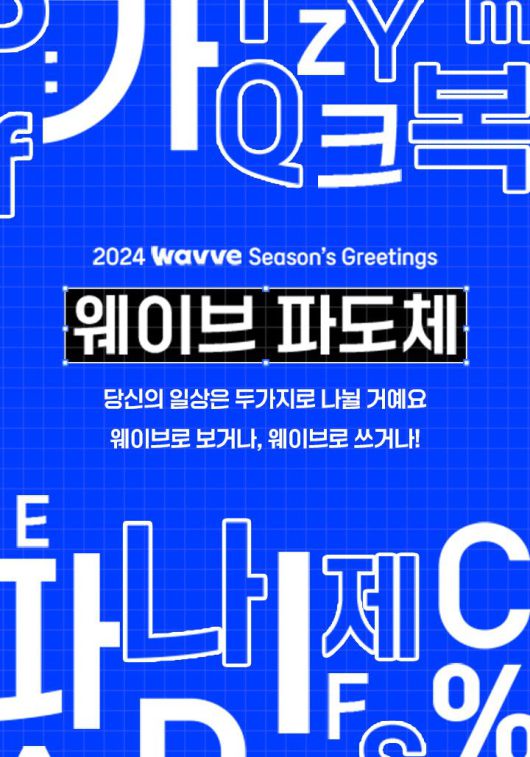
웨이브(Wavve)가 온라인 동영상 서비스(OTT) 업계 최초 브랜드 폰트 '웨이브 파도체'를 출시하고 무료 배포한다고 22일 밝혔다.
연말연시를 맞아 공개한 '웨이브 파도체'는 파도의 모양에서 영감을 얻어 좌에서 우로 향하는 획의 삐침과 곡선을 포인트로 한다. 브랜드 아이덴티티를 반영함과 동시에 콘텐츠를 즐기는 순간 이외의 일상에서 필수재인 웨이브를 더 가까이에서 만나보도록 하는 친근함의 의미를 담았다.
'웨이브 파도체'는 다이내믹이 필요한 모든 순간에 적합한 서체로, 한글 기본 2350자, 한글 특수 11자, 라틴 기본 95자, 특수 기호 269자까지 구현해 일상적인 표준 단어 표현이 가능하다.
웨이브 유혁 브랜드마케팅 팀장은 "파도체는 사실 웨이브 브랜드 필름, 로고 등 이미 다양한 분야에서 타이포그래피 형태로 자주 사용되고 있었다”며 “그동안 꾸준히 폰트 제작에 대한 성원이 있었기에 일상에서 더 많은 분들이 자유롭게 사용하실 수 있도록 만들게 됐다"고 말했다.